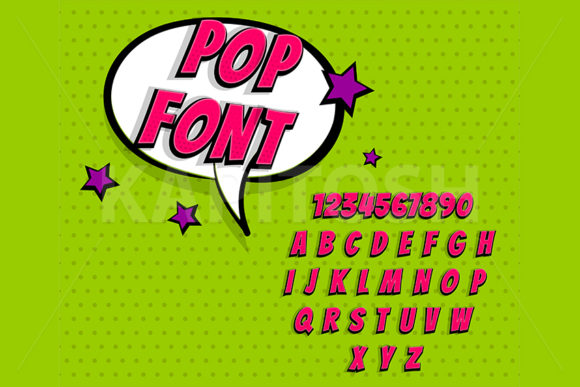
Pink Lowercase and Uppercase Comic Font
Die richtigen Designelemente zu finden, kann eine Herausforderung sein, aber Pink Lowercase and Uppercase Comic Font bietet eine außergewöhnliche Sammlung, die Ihre Arbeit sofort aufwertet.
Egal, ob Sie POD-Produkte (Print on Demand), Hochzeitseinladungen oder Social-Media-Grafiken erstellen, Pink Lowercase and Uppercase Comic Font ist die ideale Wahl.